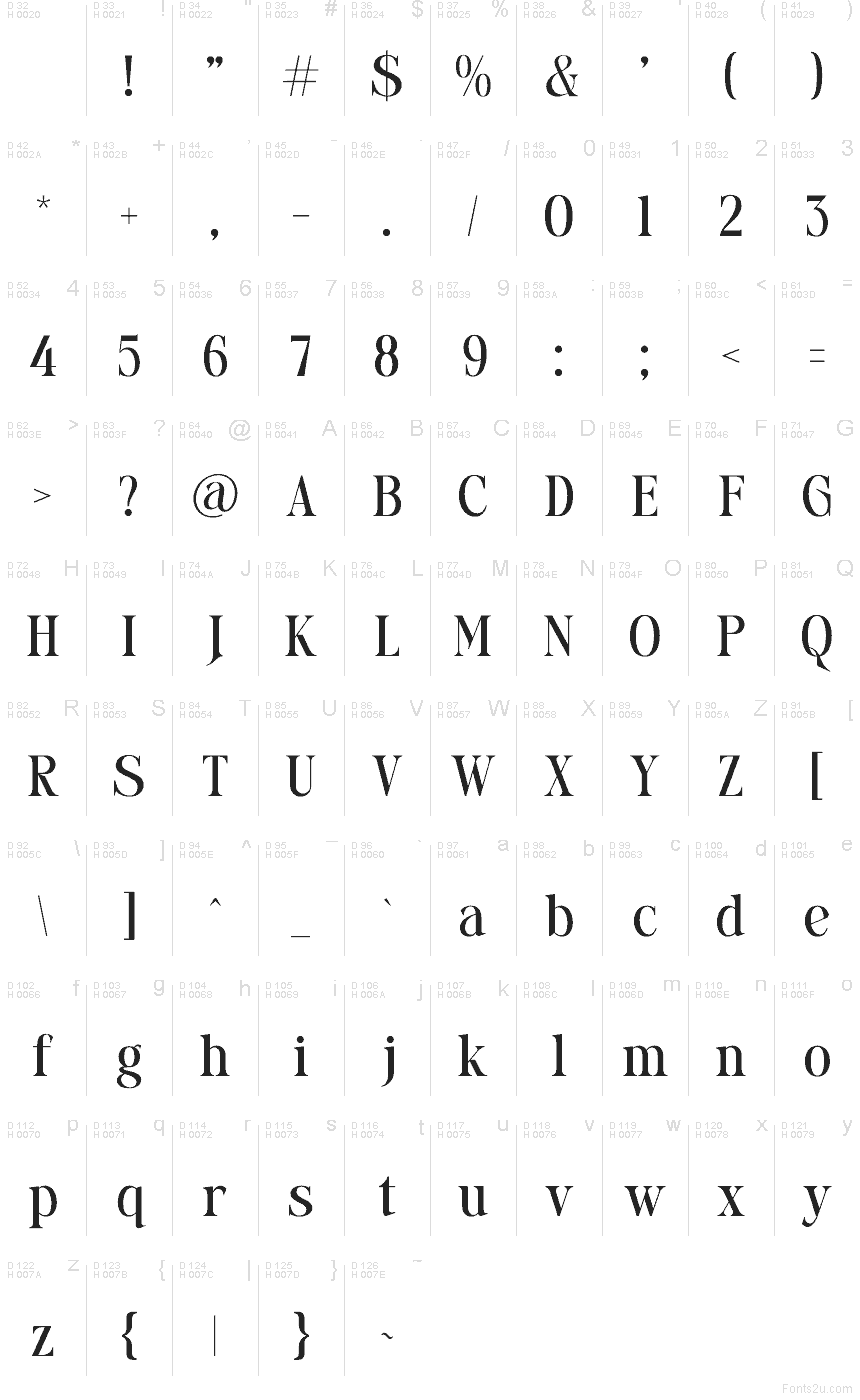
Stories Grand par TimelessType est une police serif gratuite à fort contraste, empreinte d'une élégance moderne et classique inspirée par l'univers de la mode. Le tracé s'appuie sur des contrastes marqués et des courbes fluides, tandis que ses empattements hauts et délicats lui confèrent une assurance raffinée, sans jamais paraître chargée.
Elle est parfaite pour le branding, les manchettes de magazines, les couvertures de livres, la papeterie d'invitation et les emballages de produits de beauté ou de joaillerie, où sa tension sophistiquée suffit à elle seule à mettre en valeur une ligne de texte. En tant que police gratuite, elle est également idéale pour des cartons-titres, des citations mises en avant ou des initiales façon monogramme, surtout lorsque vous recherchez un style à la fois élégant et dramatique.